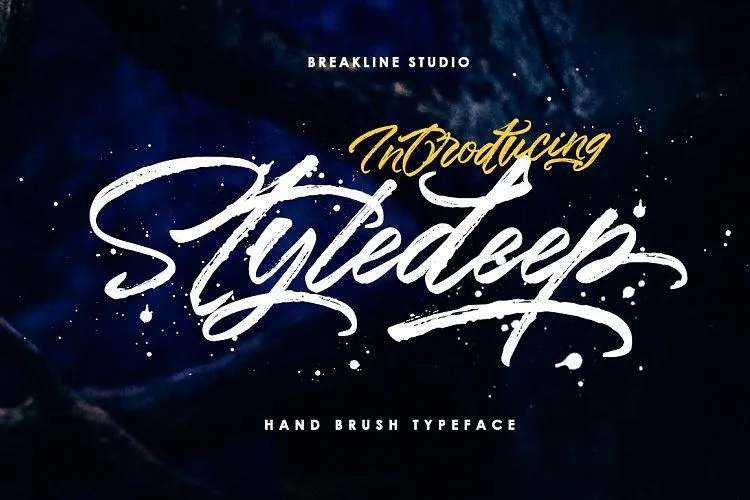
Styledeep Brush Font
Introduzimos a Styledeep Font, uma nova fonte de traço manual com estilo elegante, criada pela designer 0001themes. Esta é uma fonte feita à mão com um traçado que remete a um estilo de tinta seca e raspagem, mas ainda assim, mantém uma aparência cool. Ideal para várias necessidades de design promocional, empresariais ou decorativas. A Styledeep brilha em camisetas, panfletos e stickers, é perfeita para blogs de moda estilosos ou livros culinários, e pode ser usada em qualquer tipo de mensagem que requer uma letra assertiva. É um hit quando se trata de cabeçalhos grandes e fortes, dando seu melhor em logomarcas dinâmicas, além de expressar acentos culturais bem central europeus. Com certeza você encontrará na Styledeep Font aquela font que tanto almeja para dar vida ao design que está criando. Sem dúvidas será uma escolha inteligente para qualquer designer em busca de novas possibilidades e estilo.